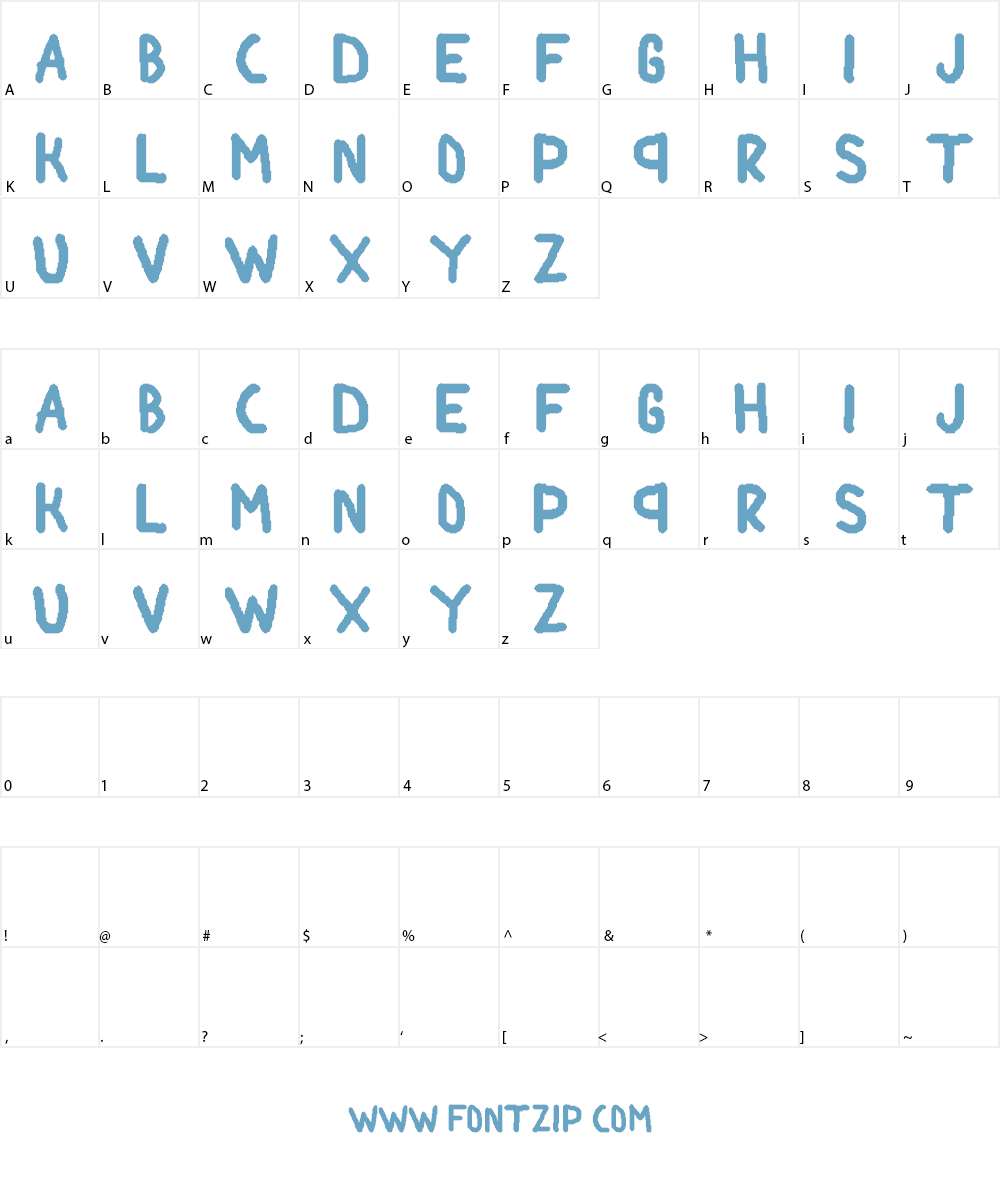
Una fuente creada únicamente con paint.. bueno una de las fuentes subidas a fontspace fueron creadas a traves de paint te explicó...
Inicie paint, hice las letras, las copie con Recortes de Windows y lo pegué a FontCreator 11.0